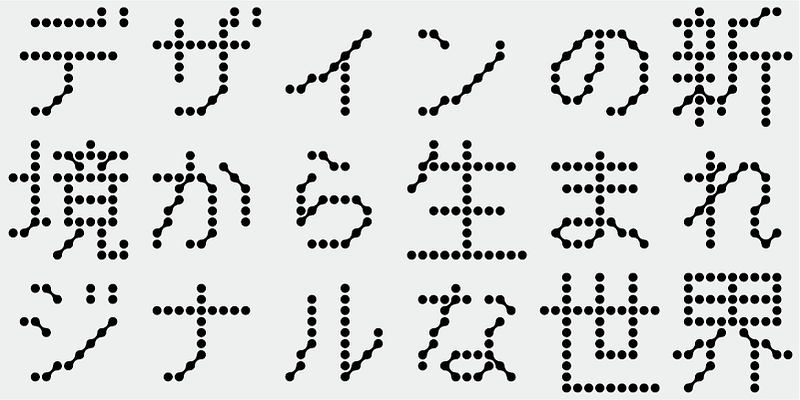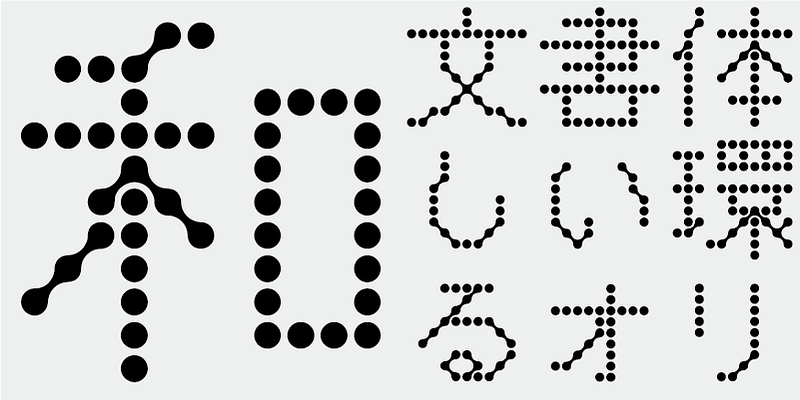
Innerhalb des Rasters von 11 x 11, das zur Vereinfachung verwendet wird, bleibt ein gutes Maß an Lesbarkeit erhalten. Die Punkte verbinden sich im 45-Grad-Winkel und bilden so ein sich ausdehnendes Netzwerk von Neuronen.
Diese Schrift wurde mit einem TDC Annual Award ausgezeichnet.
Diese Schrift enthält die 1.000 wichtigsten Kanji-Zeichen, die aus den Häufigkeitstabellen von Zeitungsunternehmen, Verlagen und linguistischen Forschungsinstituten ausgewählt wurden, sowie 206 Kana-Zeichen und Satzzeichen.
In der heutigen japanischen Schriftproduktion gelten die 7.000 Zeichen des JIS-Standards als unabdingbar. Aber brauchen alle Schriften wirklich 7.000 Zeichen? Im Zeitalter des Fotosatzes wurden weit weniger Zeichen benötigt. FONT1000, eine Gruppe unabhängiger Schriftdesigner, ging von dieser einfachen Frage aus. Wir haben die mindestens 1.000 (ideografischen) Kanji-Zeichen ausgewählt, die für den Satz in Japanisch erforderlich sind, und aktiv Schriften und Schriftbilder dafür entworfen. Dieser 1000-Kanji-Zeichensatz wurde unter Verwendung von Zeichenhäufigkeitsdaten ausgewählt, die u. a. von Zeitungsunternehmen, Verlagen und Sprachforschungsinstituten zusammengestellt wurden, und enthält auch Kana-Silbenzeichen und Satzzeichen. FONT1000 begann 2001 mit 25 Designern und 25 Schriften. Heute haben wir 130 Schriften und sind auf fast 40 Mitglieder angewachsen, sodass wir an Schriften mit mehr Zeichen arbeiten können.